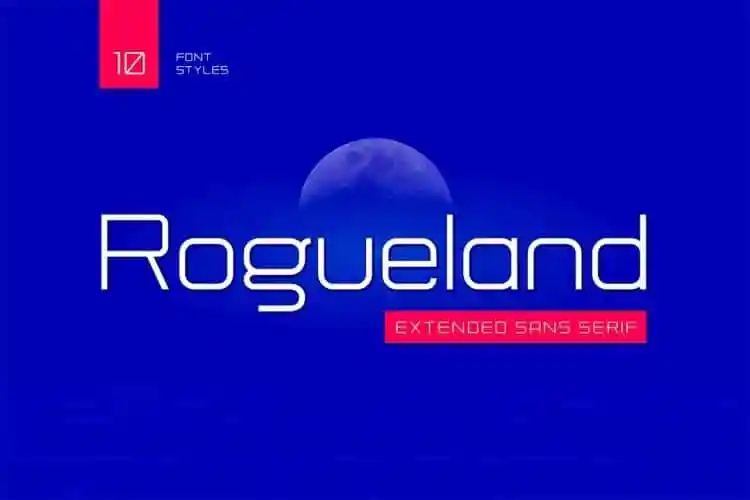
Rogueland Sans Serif Font – Download Grátis
A Rogueland Sans Serif é uma fonte moderna com um toque geométrico que se destaca na categoria de fóntes sem serif. Foi criada por Namara Creative Studio, uma equipe de designers que vislumbra a versatilidade do tipo moderno e sofisticado. Com sua estética futurista e sua proporção equilibrada entre ângulos aparentemente rígidos e curvas suaves, esta fonte é um ótimo escolha para uso em diferentes contextos. Suas linhas luxuosas são perfeitas tanto para títulos quanto para o corpo do texto, tornando-a uma opção ideal para design de sites, publicações impressas e até mesmo conteúdo digital. Com seu tom clean e moderno, a Rogueland Sans Serif é perfeitamente adaptada para headlines poderosas que exigem ressaltos visuais impactantes. A sua versatilidade faz dela uma ótima escolha para ambientes digitais ou físicos, desde redes sociais até revistas de luxo. Uma combinação arquitetônica e elegante, a Rogueland Sans Serif é uma fonte moderna, sofisticada e pronta para qualquer projeto que você possa pensar.